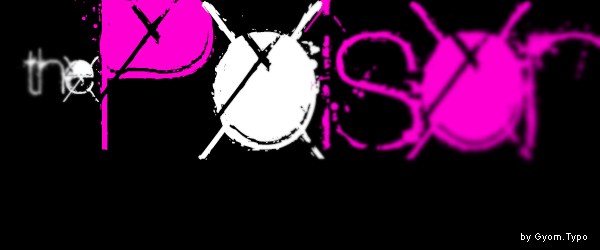
The Poison od Gyom.Typo to darmowy, erodowany krój typu display o brudnym, zniszczonym charakterze, który przywodzi na myśl punkowe ulotki i miejskie graffiti. Litery łączą cienkie kreski z ciężkimi plamami i surowymi, ukośnymi cięciami, przez co całość wygląda jak napis, który był drapany, stemplowany i niszczał z upływem czasu.
Pasuje do plakatów, okładek albumów, ulotek klubowych, horrorów i grafiki streetwearowej, gdzie potrzebna jest czcionka o surowym, „uszkodzonym” klimacie, a nie schludny krój. Użyj jej do krótkich nagłówków, tekstów na okładki czy logotypów, ponieważ te poszarpane sylwetki i przekreślenia błyskawicznie budują nastrój.